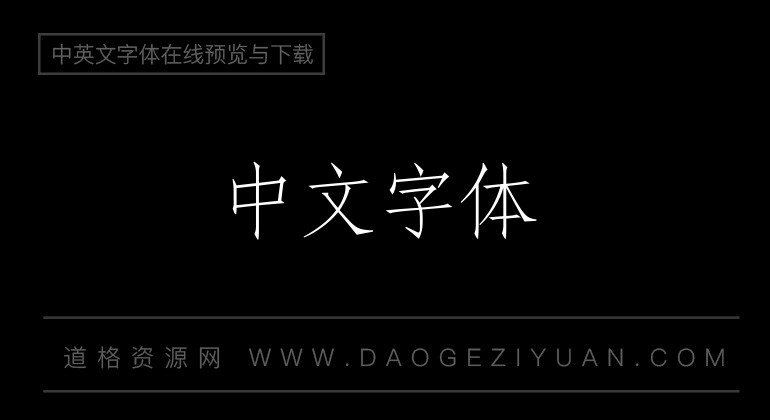
华康俪宋繁是一款简繁体混合字体,由著名字体设计师梁静茹设计,以华康俪宋字体为基础,在简体部分添加繁体符号,以满足港台地区的字体需求。它具有视觉上的优势,可以让文本更加清晰、精细。此外,它还具有良好的识别度,可以更好地展示文字,让文字看起来更加精致。文件名:HuaKangSongStdW5-1.otf
华康俪宋繁是一款非常不错的手写艺术字体,具有很好的视觉感,适合于文化类的宣传设计、商业类品牌的广告和产品包装设计以及个性化文字排版等较多场景。